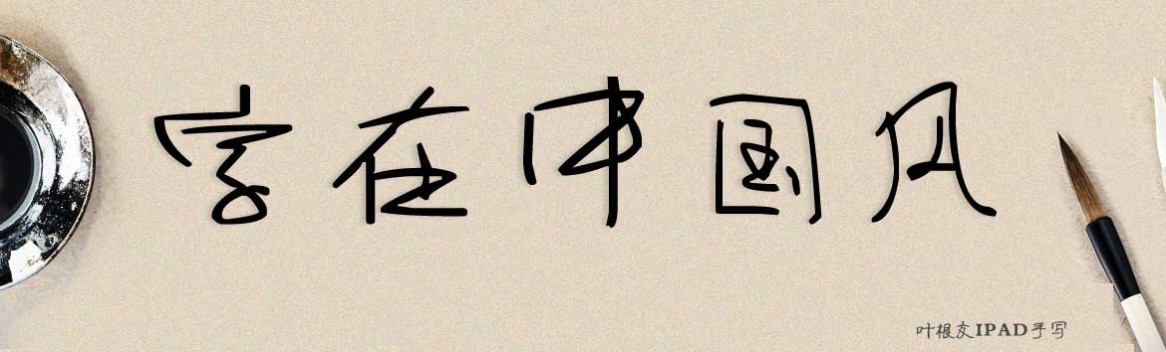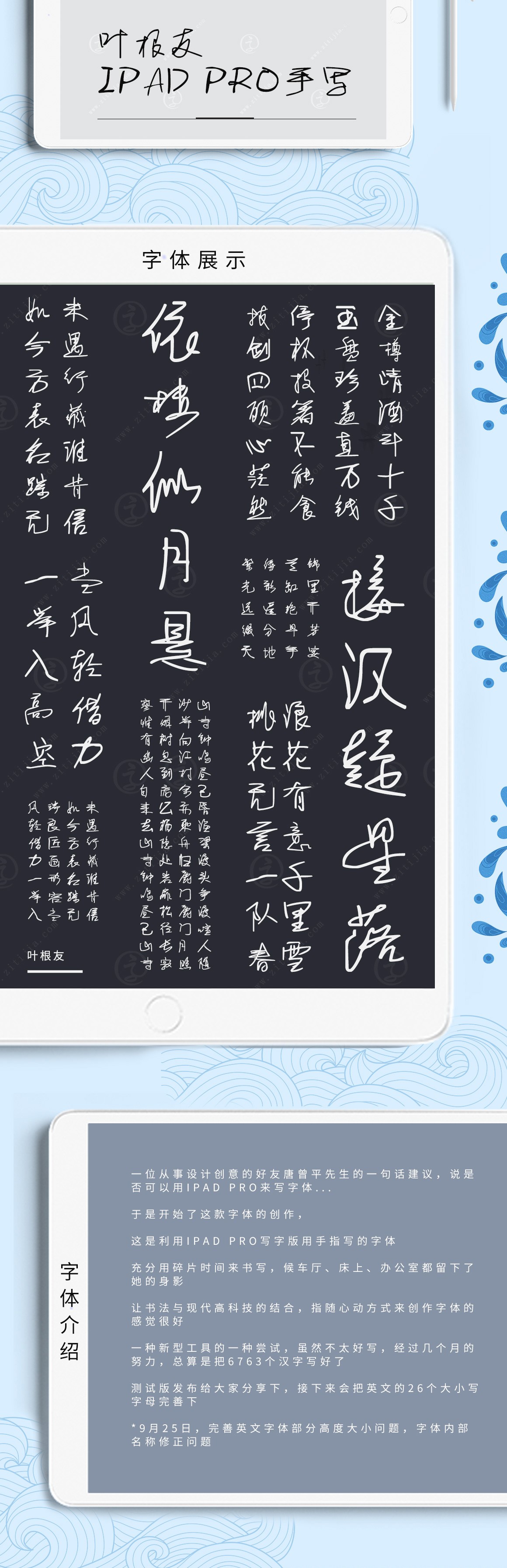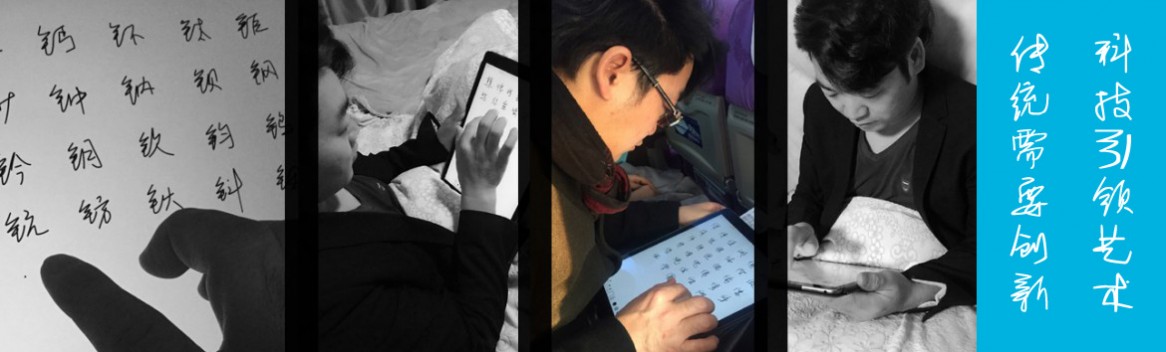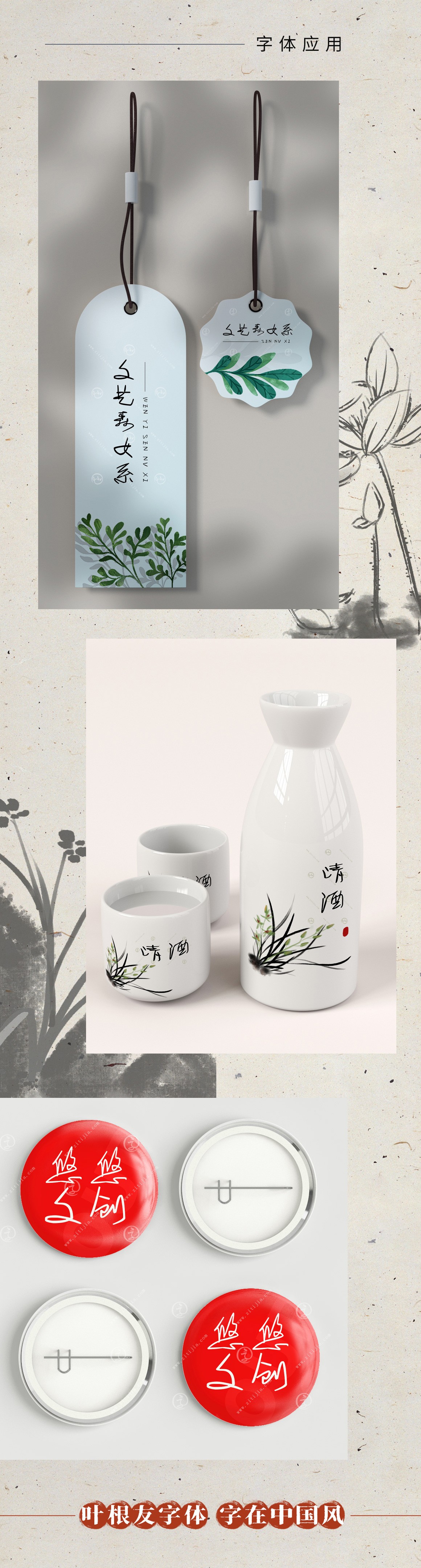
葉根友IPAD手寫體
字體作者:葉根友
創(chuàng)作年代:2015年
字體字?jǐn)?shù):6763個(gè)中文漢字以及其他英文字母和阿拉伯?dāng)?shù)字
字體介紹
一位從事設(shè)計(jì)創(chuàng)意的好友唐曾平先生的一句話建議,說是否可以用ipad pro來寫字體...
于是開始了這款字體的創(chuàng)作,
這是利用ipad pro寫字版用手指寫的字體
充分用碎片時(shí)間來書寫,候車廳、床上、辦公室都留下了她的身影
讓書法與現(xiàn)代高科技的結(jié)合,指隨心動(dòng)方式來創(chuàng)作字體的感覺很好
一種新型工具的一種嘗試,雖然不太好寫,經(jīng)過幾個(gè)月的努力,總算是把6763個(gè)漢字寫好了
測(cè)試版發(fā)布給大家分享下,接下來會(huì)把英文的26個(gè)大小寫字母完善下
*9月25日,完善英文字體部分高度大小問題,字體內(nèi)部名稱修正問題